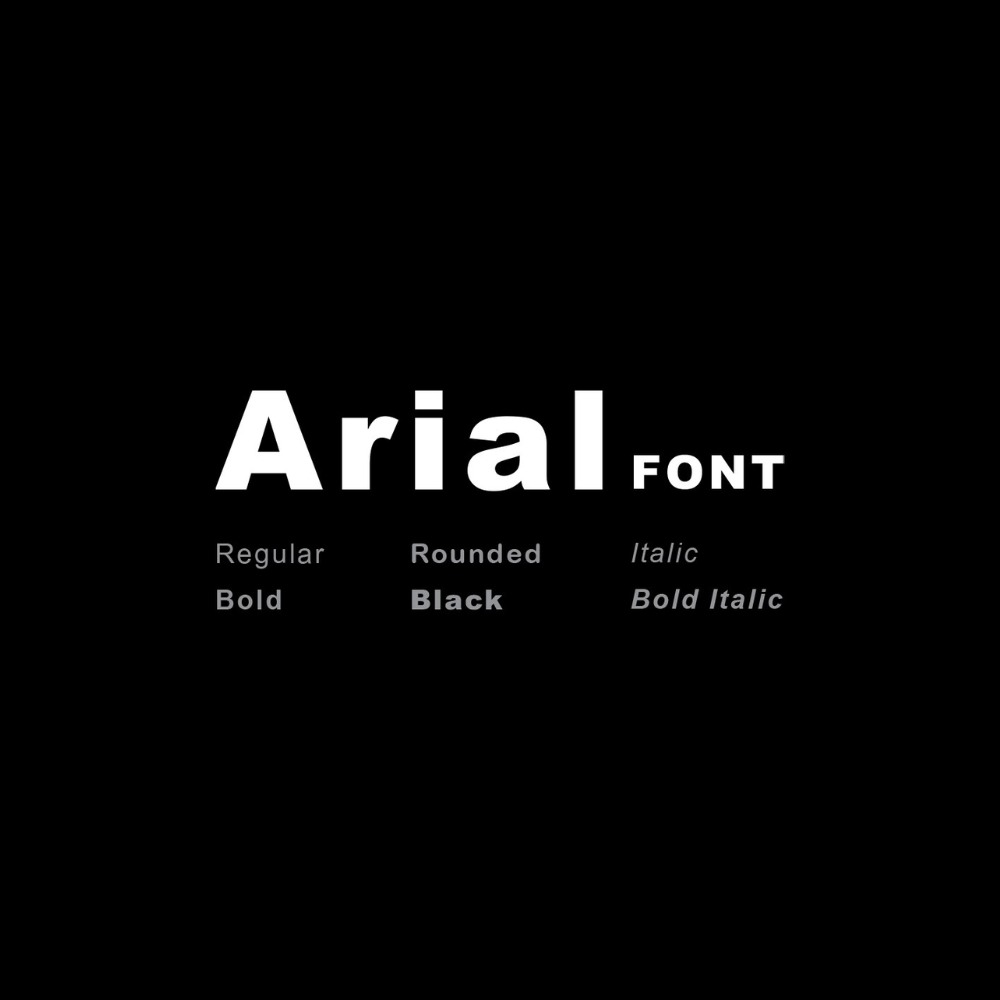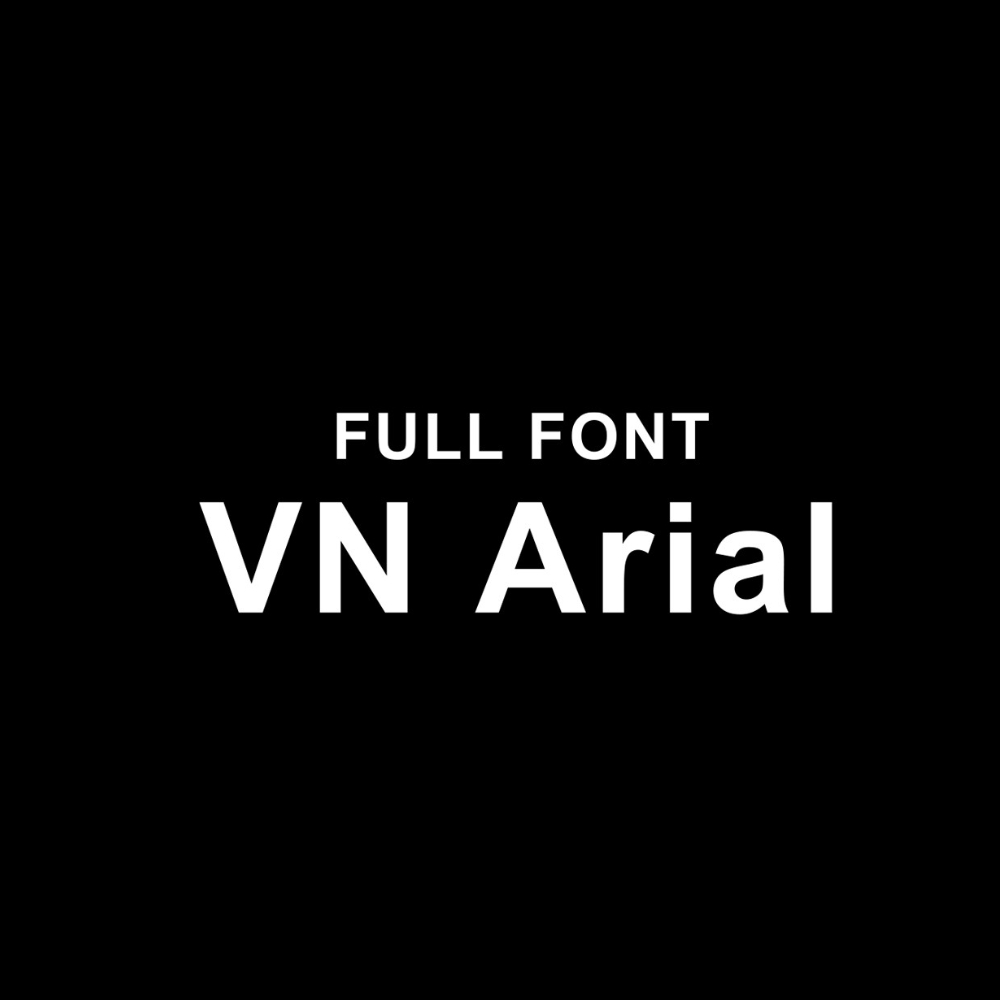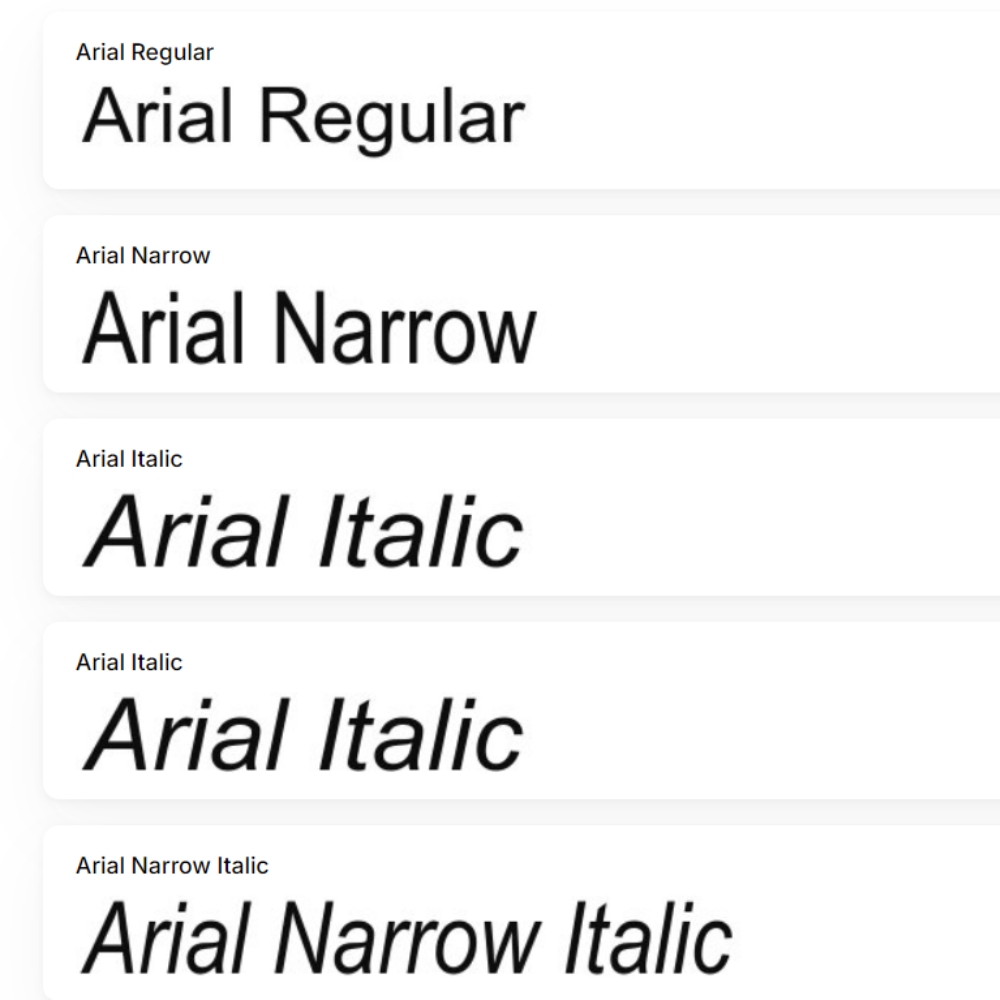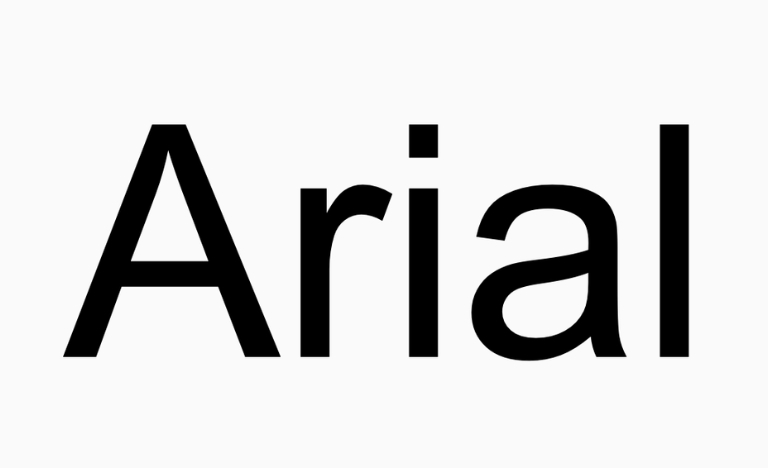
Arial download font miễn phí – font chữ phổ biến nhất thế giới được sử dụng rộng rãi trong thiết kế bao bì sản phẩm, túi giấy, tài liệu văn phòng và in ấn thương mại. Font Arial với phong cách sans-serif trung tính, rõ ràng là lựa chọn an toàn cho mọi ngành hàng và mọi loại tài liệu in.
Font Arial là gì?
Font Arial được thiết kế bởi Robin Nicholas và Patricia Saunders cho hãng Monotype năm 1982, ban đầu với tên gọi Sonoran Sans Serif. Năm 1992, Microsoft đưa Arial vào hệ điều hành Windows 3.1 như một thay thế miễn phí cho Helvetica, và từ đó Arial trở thành một trong những font chữ được sử dụng nhiều nhất trên thế giới.
Arial thuộc họ sans-serif neo-grotesque, có phong cách tương tự Helvetica nhưng với một số điểm khác biệt nhỏ về hình dạng ký tự. Font này có đặc điểm trung tính, rõ ràng, dễ đọc và phù hợp cho hầu hết mọi mục đích từ văn bản công sở đến thiết kế thương mại.
Các phiên bản Arial chính:
- Arial Regular: Phiên bản chuẩn, font mặc định của Microsoft Office, dùng cho mọi loại tài liệu văn phòng.
- Arial Bold: Phiên bản đậm, dùng cho tiêu đề, heading, tên sản phẩm trên bao bì.
- Arial Italic: Phiên bản nghiêng, dùng cho trích dẫn, nhấn mạnh, ghi chú.
- Arial Bold Italic: Kết hợp đậm và nghiêng, dùng cho nhấn mạnh đặc biệt.
- Arial Narrow: Phiên bản thu hẹp, chiều rộng ký tự hẹp hơn 18%, tiết kiệm không gian trên nhãn sản phẩm.
- Arial Unicode MS: Phiên bản mở rộng hỗ trợ hơn 50,000 ký tự từ 100+ ngôn ngữ, bao gồm tiếng Việt đầy đủ, chữ Hán, chữ Nhật, chữ Ả Rập…
- Arial Black: Phiên bản cực đậm, dùng cho poster, billboard, tiêu đề lớn.
- Arial Rounded MT Bold: Phiên bản bo tròn các góc, tạo cảm giác thân thiện, dễ thương.
Arial có sẵn trên hầu hết máy tính Windows và Mac, là font hệ thống mặc định của Microsoft Office (Word, Excel, PowerPoint).
Tên phiên bản |
Đặc điểm |
Ứng dụng in ấn tốt nhất |
Arial Regular |
Sans-serif chuẩn | Mô tả sản phẩm, thông tin bao bì, tài liệu (8-12pt). |
Arial Bold |
Đậm, nổi bật | Tên sản phẩm, logo, tiêu đề túi giấy (14-24pt). |
Arial Narrow |
Thu hẹp 18% | Nhãn sản phẩm nhỏ, tiết kiệm không gian. |
Arial Unicode MS |
Hỗ trợ 50,000+ ký tự | Sản phẩm xuất khẩu đa ngôn ngữ, bao bì quốc tế. |
Arial Black |
Cực đậm | Poster, billboard, standee khổ lớn. |
Arial Rounded MT Bold |
Bo tròn, thân thiện | Sản phẩm trẻ em, đồ chơi, thực phẩm vui tươi. |
Ứng dụng font Arial trong thiết kế bao bì và văn phòng
Font Arial mang phong cách trung tính, an toàn, được ưa chuộng trong mọi lĩnh vực:
- Font mặc định của Microsoft Office: Arial là font mặc định cho Word, Excel, PowerPoint, khiến nó trở thành font quen thuộc nhất trong môi trường văn phòng và kinh doanh.
- Trung tính tuyệt đối: Giống Helvetica, Arial không mang phong cách riêng biệt nào, phù hợp cho mọi ngành hàng từ thực phẩm, dược phẩm, công nghệ đến thời trang.
- Dễ đọc, rõ ràng: Các nét chữ Arial rõ ràng, khoảng cách ký tự vừa phải, giúp thông tin sản phẩm dễ đọc ngay cả khi in kích thước nhỏ.
- Tương thích cao: Vì Arial có sẵn trên mọi máy tính, file thiết kế dùng Arial dễ dàng trao đổi giữa các bên mà không lo lỗi font.
Font Arial xuất hiện rộng rãi trong nhiều sản phẩm in ấn:
- Bao bì sản phẩm đa ngành: thực phẩm, dược phẩm, mỹ phẩm, hóa chất.
- Túi giấy doanh nghiệp: túi kraft, túi couche in logo với Arial Bold.
- Nhãn sản phẩm, tem mác: thông tin thành phần, hướng dẫn sử dụng với Arial Regular.
- Tài liệu văn phòng in ấn: hợp đồng, công văn, báo cáo với Arial.